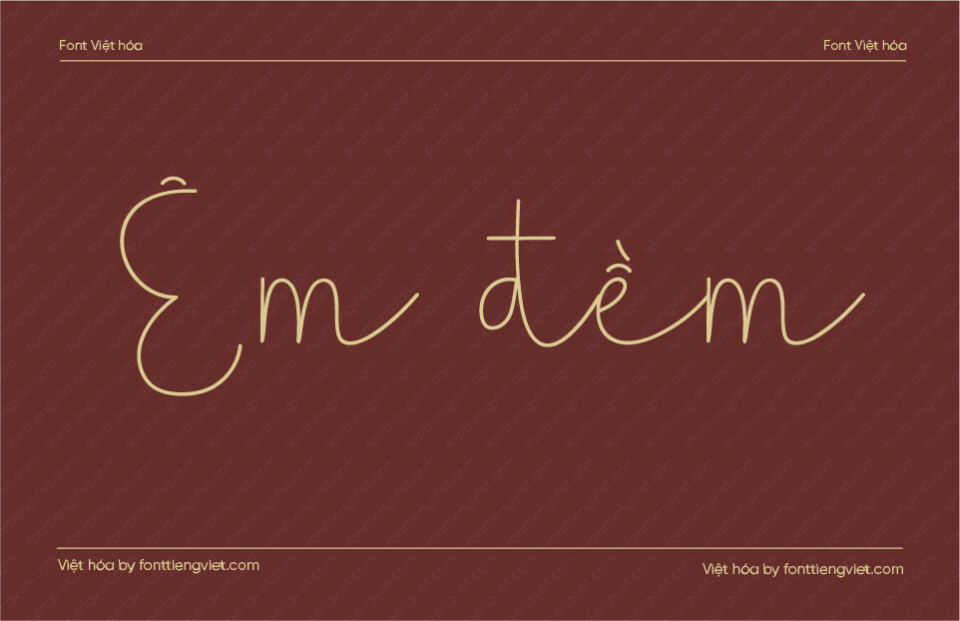
Font Việt hóa 1FTV VIP Stocking – Font chữ ký đẹp chuyên nghiệp cho thiết kế
Giới thiệu về Font Việt hóa 1FTV VIP Stocking – Font chữ ký đẹp
Trong thế giới đồ họa hiện đại, việc tìm kiếm một bộ Font Chữ mang đậm dấu ấn cá nhân luôn là ưu tiên hàng đầu của các nhà thiết kế. Font Việt hóa 1FTV VIP Stocking – Font chữ ký đẹp xuất hiện như một giải pháp hoàn hảo dành cho những ai yêu thích sự mềm mại, uyển chuyển và tinh tế. Bộ font này không chỉ đơn thuần là các ký tự mà còn là một tác phẩm nghệ thuật, mô phỏng chân thực nét bút viết tay của con người. Đặc biệt, phiên bản 1FTV VIP Stocking đã được việt hóa hoàn chỉnh, giúp người dùng dễ dàng sử dụng trong các phần mềm thiết kế mà không lo lỗi dấu hay khoảng cách chữ.
Tại sao nên chọn bộ font chữ ký này cho giáo dục và văn phòng?
Bộ font này cực kỳ phù hợp với môi trường học đường và giáo dục bởi phong cách thanh lịch, dễ nhìn nhưng vẫn giữ được nét độc đáo. Các giáo viên có thể dùng để thiết kế thiệp mời, bằng khen hoặc trang trí bài giảng điện tử sinh động hơn. Với cấu trúc đường nét thanh mảnh, 1FTV VIP Stocking giúp nội dung trở nên gần gũi và chuyên nghiệp hơn bao giờ hết.
Đặc điểm nổi bật và ứng dụng của Font Việt hóa 1FTV VIP Stocking – Font chữ ký đẹp
Điểm mạnh nhất của bộ font này chính là sự cân bằng giữa tính thẩm mỹ và khả năng đọc. Các ký tự được liên kết với nhau một cách tự nhiên, tạo cảm giác như được viết bằng bút mực thật trên giấy cao cấp. Ngoài ra, tính năng hiển thị tốt trên cả nền tảng in ấn và kỹ thuật số khiến nó trở thành lựa chọn số một cho các dự án thương hiệu cá nhân.
Ứng dụng thực tế trong thiết kế đồ họa
Người dùng có thể ứng dụng font chữ này vào việc thiết kế logo, bìa sách, ảnh bìa mạng xã hội hoặc các loại thiệp cưới, thiệp chúc mừng. Sự tinh tế của các nét uốn lượn sẽ làm nổi bật tên riêng hoặc các thông điệp quan trọng, tạo ấn tượng mạnh mẽ với người xem ngay từ cái nhìn đầu tiên.
Kết luận về bộ Font Việt hóa 1FTV VIP Stocking – Font chữ ký đẹp